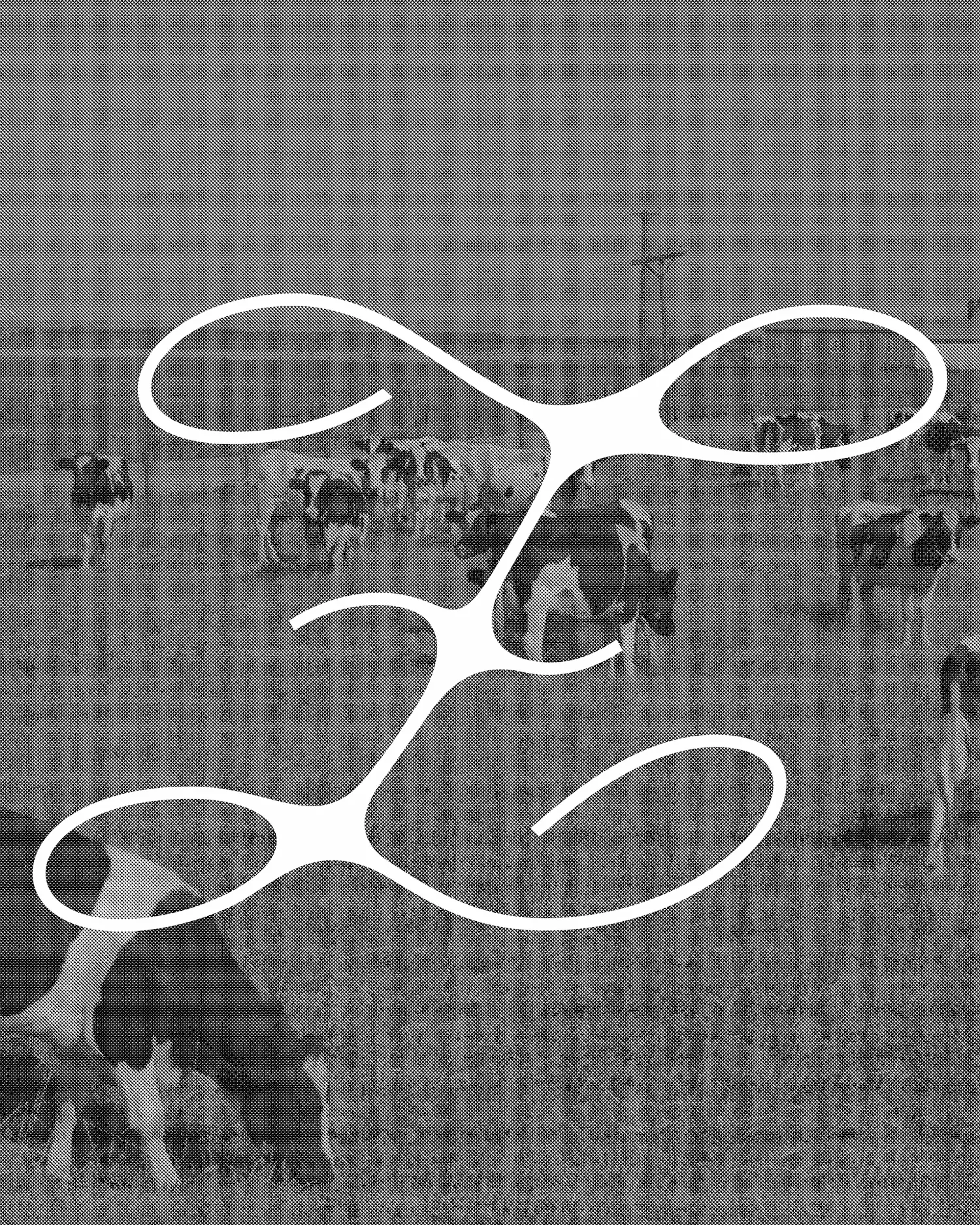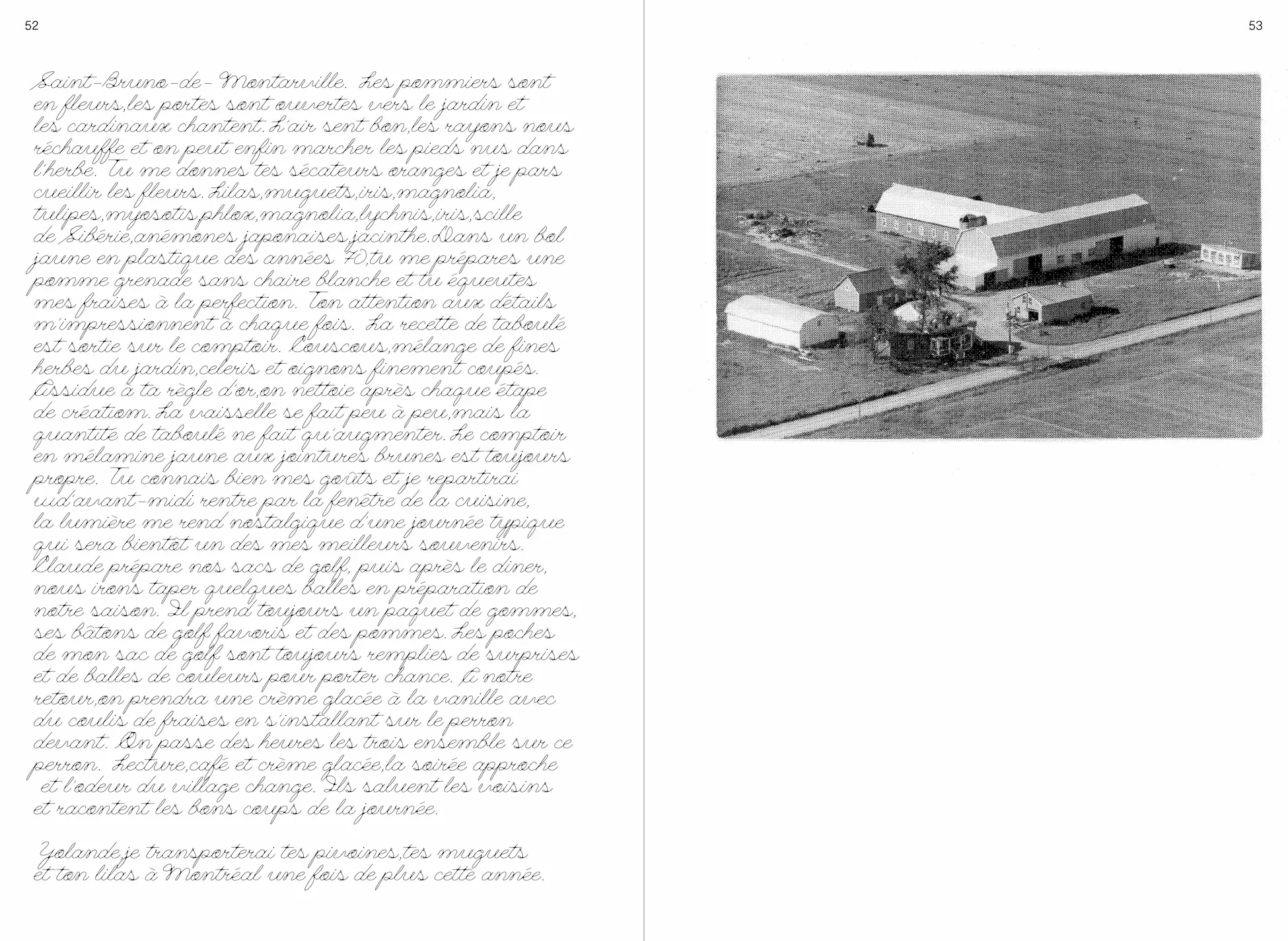
Yolande est une police de caractères qui rend hommage aux femmes québécoises de la génération silencieuse (1925-1945) en s’inspirant de leurs codes calligraphiques manuscrits. En réalisant que les femmes de cette génération ont une manière d’écrire similaire, ce travail veut s’inspirer et immortaliser cette calligraphie historique avant qu’elle ne s’efface complètement avec sa génération. De nature italique et cursive, cette police de caractères naît d’une recherche minutieuse et approfondie des écrits de Yolande, dispersés à travers son vécu. Ses recettes, ses lettres d’amour et ses calendriers sont remplis d’annotations laissées par une Yolande qui n’a pas toujours eu 95 ans. Chaque caractère de sa calligraphie a été analysé et répertorié, créant ainsi des codes et des similitudes. Les caractères de la police se construisent à partir d’une moyenne des lettres présélectionnées et se dessinent avec une bavure à chaque intersection de traits. Inspirée d'une observation et d'une réflexion sur la calligraphie générationnelle au Québec, Yolande est une police de caractères qui rend hommage à nos grand-mères québécoises de la génération silencieuse. De nature italique et cursive, elle naît d’une analyse minutieuse et approfondie des écrits de Yolande, dispersés à travers son vécu. Les livres, les lettres d’amour, les recettes et les calendriers sont remplis d’annotations laissées par une Yolande qui n’a pas toujours eu 95 ans. Inspirée d'une réflexion sur la calligraphie des femmes de la génération silencieuse au Québec, Yolande est une police de caractères leur rendant hommage.